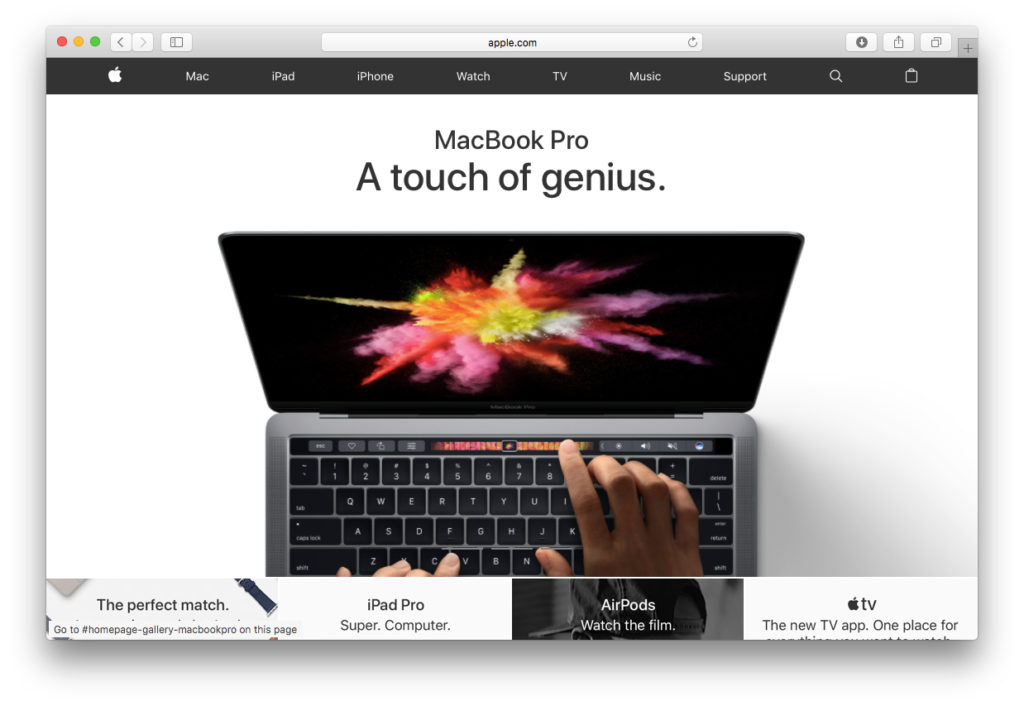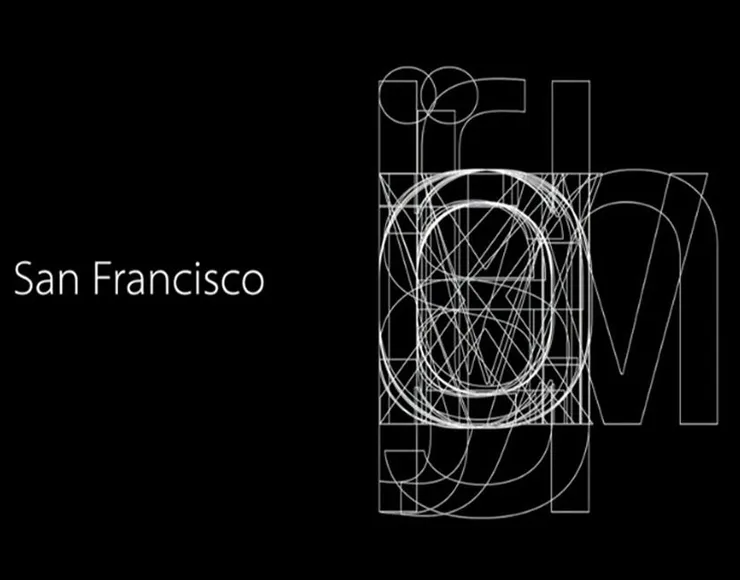
Il sito Apple cambia faccia: ora usa il font San Francisco
Apple ha cambiato il font sfruttato sul proprio sito web e anziché “Myriad” usa ora “San Francisco”. Il carattere in questione è usato sull’home page e altre pagine, una scelta che dovrebbe migliorare la leggibilità complessiva. Il carattere di Apple è arrivato con iOS 9 e adottato anche da OS X 10.11 come font di sistema. In realtà esistono due varianti del carattere: “San Francisco Display” e “San Francisco Text”. La larghezza tra le lettere nella variante Display è minore, rispetto all’altra; la prima, infatti, è pensata per l’uso con schermi più grandi, l’altra per schermi più piccoli.
Come abbiamo spiegato qui, il carattere ha un look pulito e leggibile, e vanta molti minuscoli dettagli spesso trascurati da altri font. Le lettere minuscole sono alte circa il 75% rispetto alle lettere maiuscole, in più la distanza tra le lettere è leggermente maggiore, elemento che contribuisce a renderlo più chiaro anche a dimensioni estremamente ridotte. Il suo aspetto essenziale, rende molto bene anche con gli schermi Retina.
Apple in passato ha progettato vari font ma dagli anni ’90 in poi ha lasciato il campo ad altri; “San Francisco” è una sorta di ritorno alle origini, quando Susan Kare ideò, tre le altre cose, il carattere di sistema da usare nei titoli, nelle voci di menù, nelle finestre di avviso e dialogo del Mac.